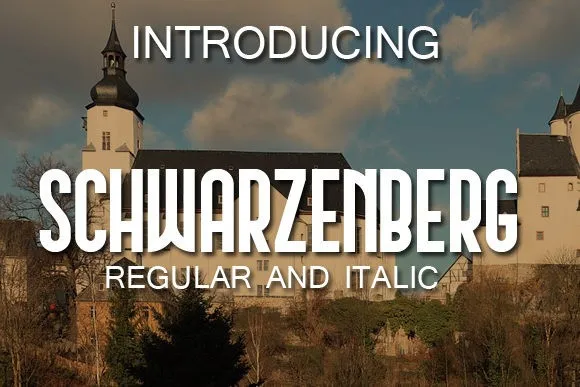
A Schwarzenberg Font é uma opção elegante para designers que desejam dar um toque vibrante a suas criações digitais sem perder seu aspecto moderno e limpo. Inspirada no rico patrimônio cultural do Tiki, esta fonte séria sem serif é perfeita para adicionar um toque criativo em posters de festa ou elementos visuais de marcas e sinalização urbanos. Suas características incluem Small Caps, símbolos tropicais incríveis que podem levar seu design a um nível ainda mais emocionante, e bordas decorativas que adicionam uma atmosfera única aos seus projetos. Seja para criar cartazes vibrantes ou elementos de layout minimalistas, esta fonte oferece o equilíbrio perfeito entre simplicidade e brilho, tornando-a uma opção inigualável para quem busca adicionar um toque especial a suas criações.